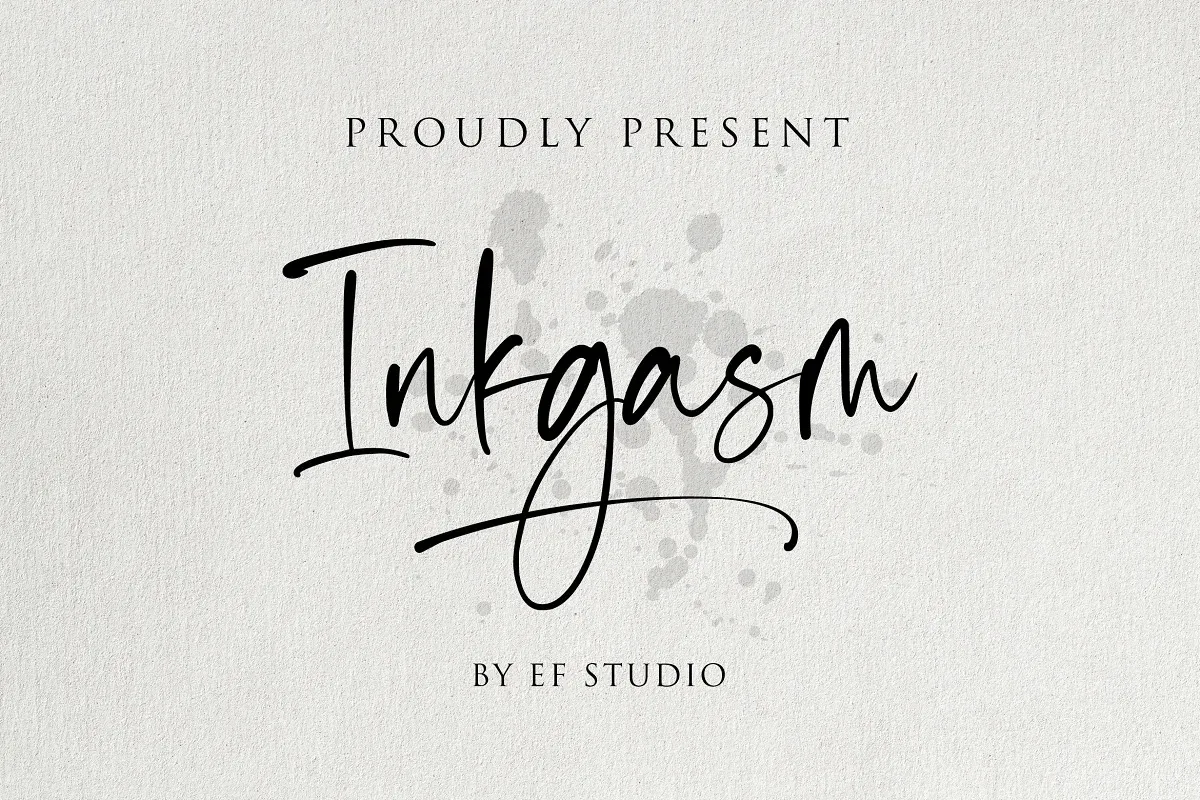
Inkgasm Font – Fonte Grátis
Inkgasm Font
A Inkgasm é uma fonte script casual que combina elegância com modernidade, criada pelo Ef Studio. Ideal para diversas aplicações gráficas, a fonte está perfeitamente adaptada para projetos como marcações, convites, merchandising, websites, anúncios e revistas. Com o conjunto completo de letras maiúsculas e minúsculas, números e pontuação, símbolos multilíngues, ligaduras e mais swashes extras, a Inkgasm se destaca como uma opção versátil para designers digitais. Seja você um criador de marcas digital ou designer gráfico, o seu trabalho vai ganhar um toque autêntico e sofisticado com essa fonte incrivelmente detalhada da Ef Studio.